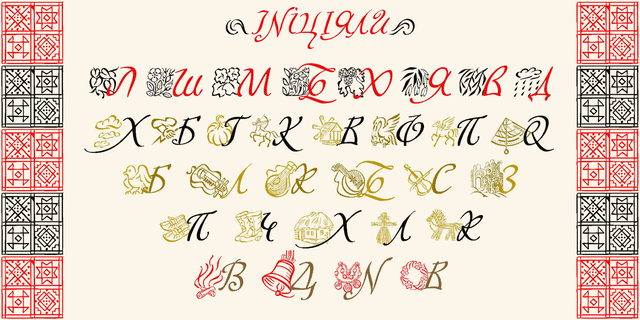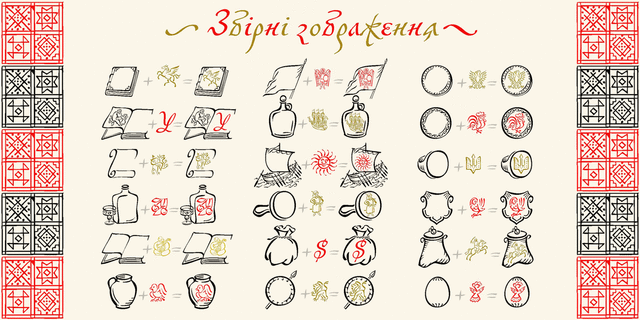
Этот шрифт является полной, исправленной и расширенной версией шрифта «Скоропись-XVII» с цифрами, полной стандартной и старой кириллицей, расширенной латиницей, греческим алфавитом и дополнительными декоративными элементами и опентайп-фичами. Следует обратить внимание, что буквы кириллицы, латиницы и гречицы способны заменять друг друга в качестве альтернатив — это дает возможность оживить строку и приблизить результат к аутентичным образцам, потому что одной из характерных черт скорописи, в частности украинской, и в то же время большой проблемой для наборного шрифта является большое разнообразие графем, которые прихотливо чередуются в тексте и создают сложный живой ритм. Такое решение позволяет простым пользователям получать желаемый результат с помощью простой таблицы глифов. Шрифт разработали Геннадий Заречнюк и Виктор Харик в 2016–2017 годах.
Skoropys17 Щедрик